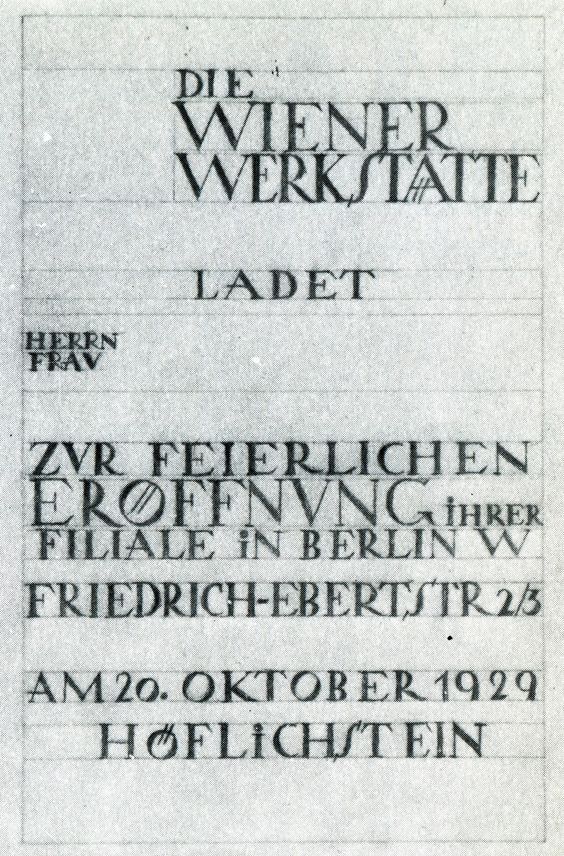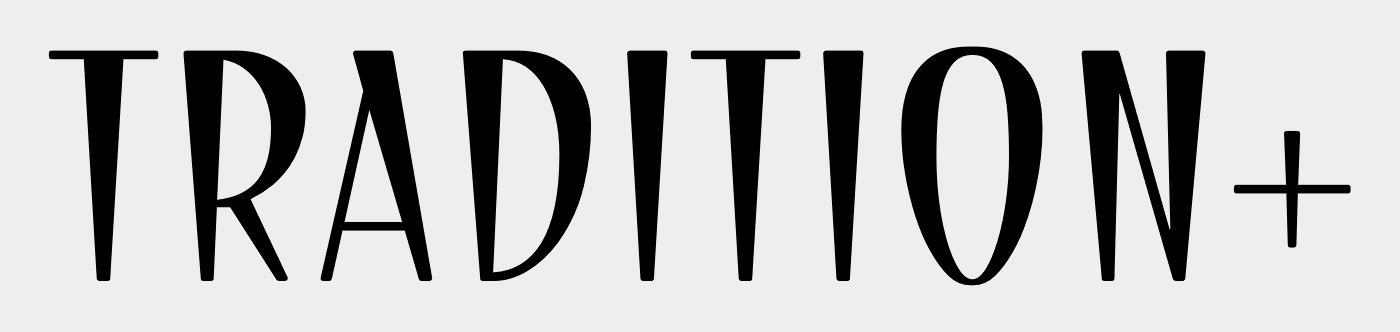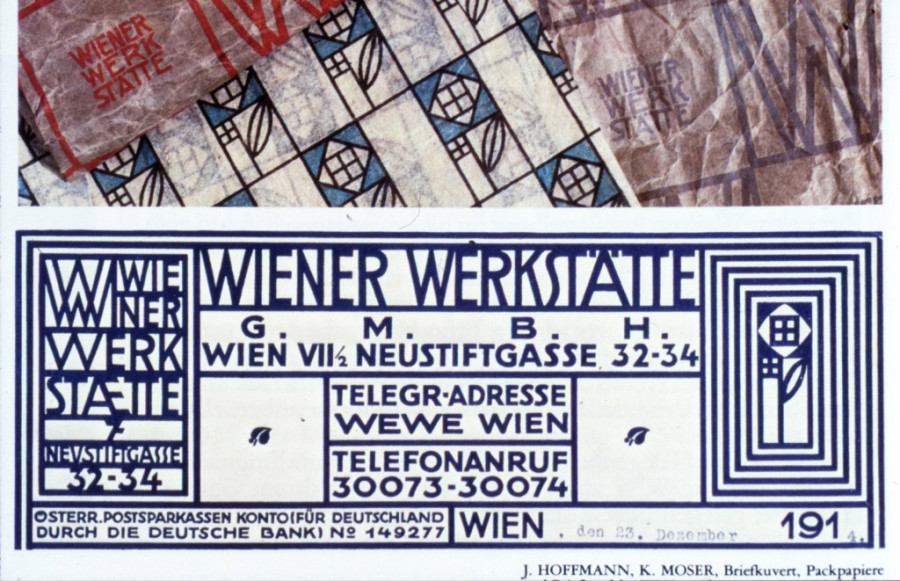
Eigenständige Schrift gesucht für Branding
Ich suche eine Schrift für ein Branding:
- es geht um ein Branding für ein Unternehmen, welches sehr hochwertige Produkte (aber die sind nicht total "clean"... also keine total klar gestalteteten Möbel oder so) in echter Handarbeit herstellt
- Kunsthandwerk im Prinzip, wobei die Produkte in ein schlichtes, zeitgemäßes Design eingebettet sein sollen
- jedes Produkt ist ein Unikat, weswegen ich überlegt habe, dass vielleicht eine Schrift mit starkem eigenständigen Charakter gut wäre, bzw. eine in der einzelne Buchstaben starke Charakterzüge haben
- ich bin noch nicht festgelegt, ob es eine serif oder eine sans-serif werden soll... oder ob ich mische. Im Prinzip soll sich das Design eher zurücknehmen, was für eine sans-serif sprechen würde. Andererseits geht es um Kunsthandwerk und es wäre vielleicht nicht schlecht eine Schrift zu haben, die das eigenständige, handwerkliche aufgreift
- im Prinzip würde eine der klassischen Grotesk Schriften auf jeden Fall funktionieren, aber vielleicht geht da ja auch mehr
- die Caslon würde rein theoretisch auch passen, aber wirkt auch einfach ein bisschen altbacken
- was ich momentan ziemlich gut finde, sind manipulierte Klassiker
- da die Produkte eher rund sind, sollte die Schrift eher runde Formen als kantige haben
- vielleicht wäre aber auch eine mit starkem Feder-Duktus was als stark kontrastierend
Ganz interessant finde ich zum Beispiel folgende Schrift:
http://www.ortype.is/specimen/landnáma
oder http://radimpesko.com/fonts/larish-neue (wobei die evtl. auch zu kantig ist... aber vom Prinzip)
oder auch ganz nett https://www.myfonts.com/fonts/bitstream/romana/
oder doch ne Grotesk mit paar Eigenheiten https://www.grillitype.com/typefaces/gt-haptik
oder http://www.alfatypefonts.com/index.html
Schau Dir doch mal die »Grund« an. Die hat eine schöne Geschichte und wurde sehr liebevoll und detailgetreu von Andreas Stötzner umgesetzt. Und sie ist eigenständig und modern – ohne modisch zu sein.
Denke auch, dass die gut zum Thema Möbel passen könnte. Aber es kommt ja am Ende die persönliche Geschmackskomponente bei der Entscheidung hinzu.
Die hatte ich beim Lesen Deiner vorhergehenden Zeilen auch im Sinn. Oder die GT Sectra, wenn Du das mit dem Feder-Duktus mal testen möchtest.
Deine Abbildungen lassen mich noch an diese Perle hier denken: Elegant Lux Pro. Bei dieser Foundry findest Du unter Umständen noch andere brauchbare Kandidaten, beispielsweise diesen: Neue Droschke.